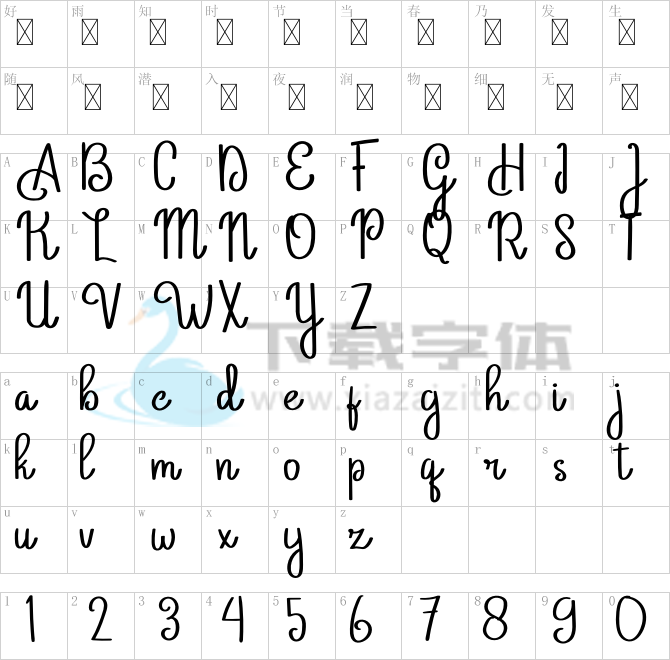
Arbiy.otf字体下载
Arbiy.otf字体下载,这款字体结构工整、笔画清晰,兼顾美观与易读性,适用于标题、正文、海报、包装、LOGO 等多种场景。字形优雅稳定,风格百搭耐看,适配日常排版与创意设计,让文字呈现更舒适、更具质感。Arbiy.otf字体下载一笔一画,皆是细节,以均衡的比例、流畅的线条打造舒适视觉体验,字形端正大气,风格简约现代。无论是商业设计、品牌宣传还是日常排版,都能轻松驾驭,让文字更有格调与力量。Arbiy.otf字体下载字体下载。